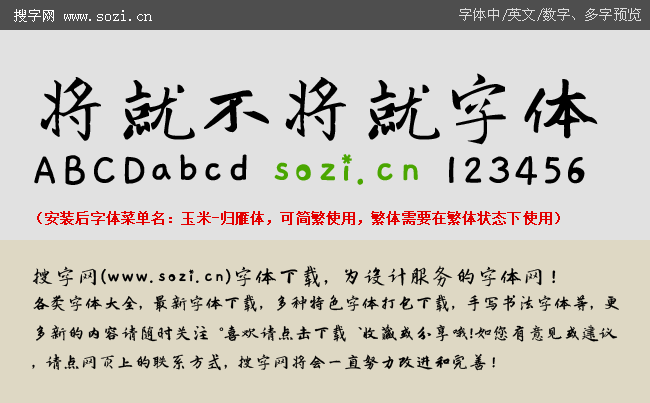
將就不將就字體
搜字網(wǎng)給大家提供一款書法風(fēng)格的將就不將就字體手機(jī)中文字體下載。這款手機(jī)字體是是以趙孟頫書法字體為原形。趙孟頫書法點(diǎn)畫華滋遒勁,結(jié)體寬綽秀美外似柔潤而內(nèi)實(shí)堅(jiān)強(qiáng),形體端秀而骨架勁挺。適合喜歡書法的朋友在手機(jī)上安裝使用。